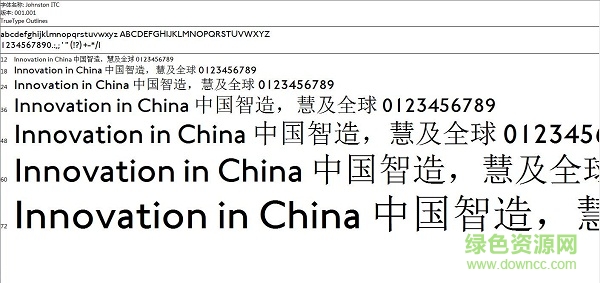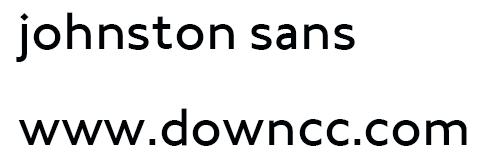
johnston sans 字體
johnston sans字體是一款超經(jīng)典的舊式無襯線字體,該字體多見于地圖標(biāo)志,比例設(shè)計精恰,外觀簡潔圓潤,用在電子屏幕上顯示效果良好,需要的朋友快來本站下載吧!
無襯線體特征
無襯線體給人一種休閑輕松的感覺。隨著現(xiàn)代生活和流行趨勢的變化,如今的人們越來越喜歡用無襯線體,因為他們看上去“更干凈”。
johnston字體